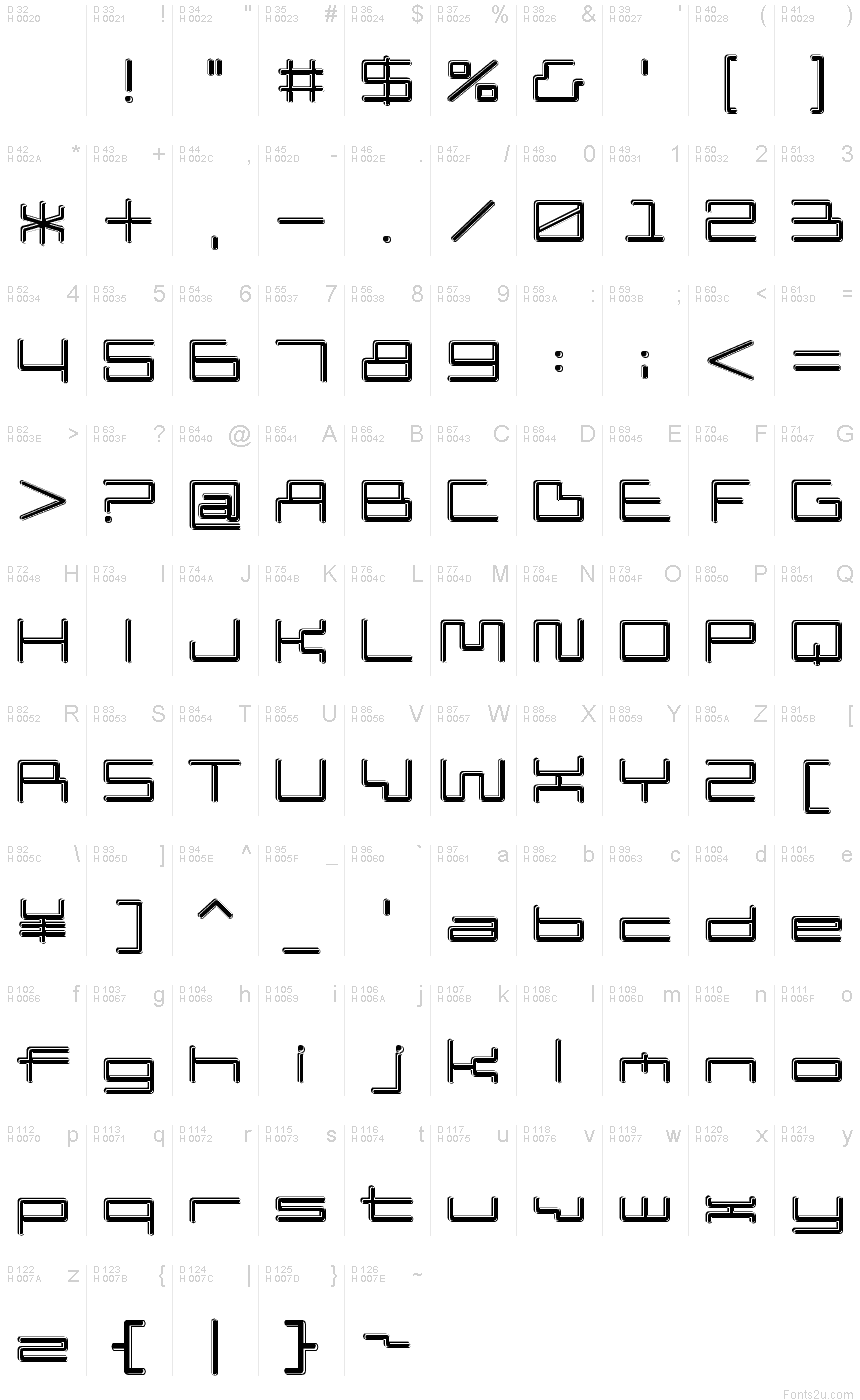
D3 PipismS autorstwa Yoshiyasu Ito to darmowy, techniczny font typu display, który wygląda jak świecące obwody drukowane wygięte w kształt liter. Rurkowe, podwójne linie, kwadratowe pętle i zaokrąglone rogi tworzą smukłą, pustą w środku strukturę, przywodzącą na myśl zarówno retro konsole, jak i neonowy klimat nocnych klubów. Jednolita grubość linii zapewnia przejrzystość, a nakładające się kontury dodają subtelnej, trójwymiarowej wibracji, która świetnie prezentuje się na ekranie.
Dzięki D3 PipismS uzyskasz wyrazisty, futurystyczny rytm, który sprawdzi się w tytułach gier sci-fi, ulotkach klubowych, plakatach w stylu vaporwave, brandingu technologicznych wydarzeń, okładkach muzycznych i makietach UI. Ten darmowy font najlepiej prezentuje się w dużym rozmiarze i z szerokim kerningiem; dla tekstów pomocniczych zestaw go z prostym, geometrycznym bezszeryfem.